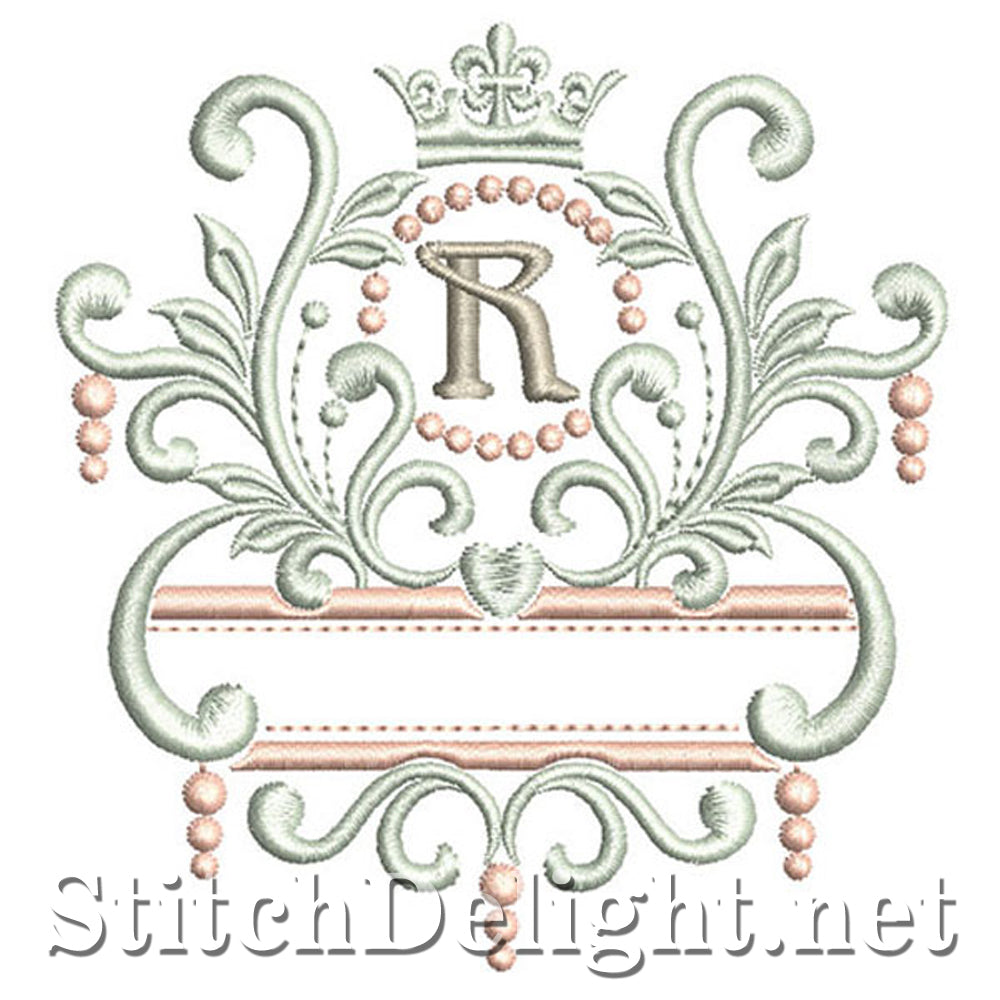
SDS1193 Elegant Royal Font R
Personalisieren Sie Ihr Projekt mit diesem stilvollen Monogramm-Set (4x4 und 5x7 Rahmengrößen inklusive sowie der BX-Version für die Embrilliance-Software - Sie können den Namen entsprechend der Initiale wie auf dem Foto mit SDS1194 (Tiny Arial Font) hinzufügen